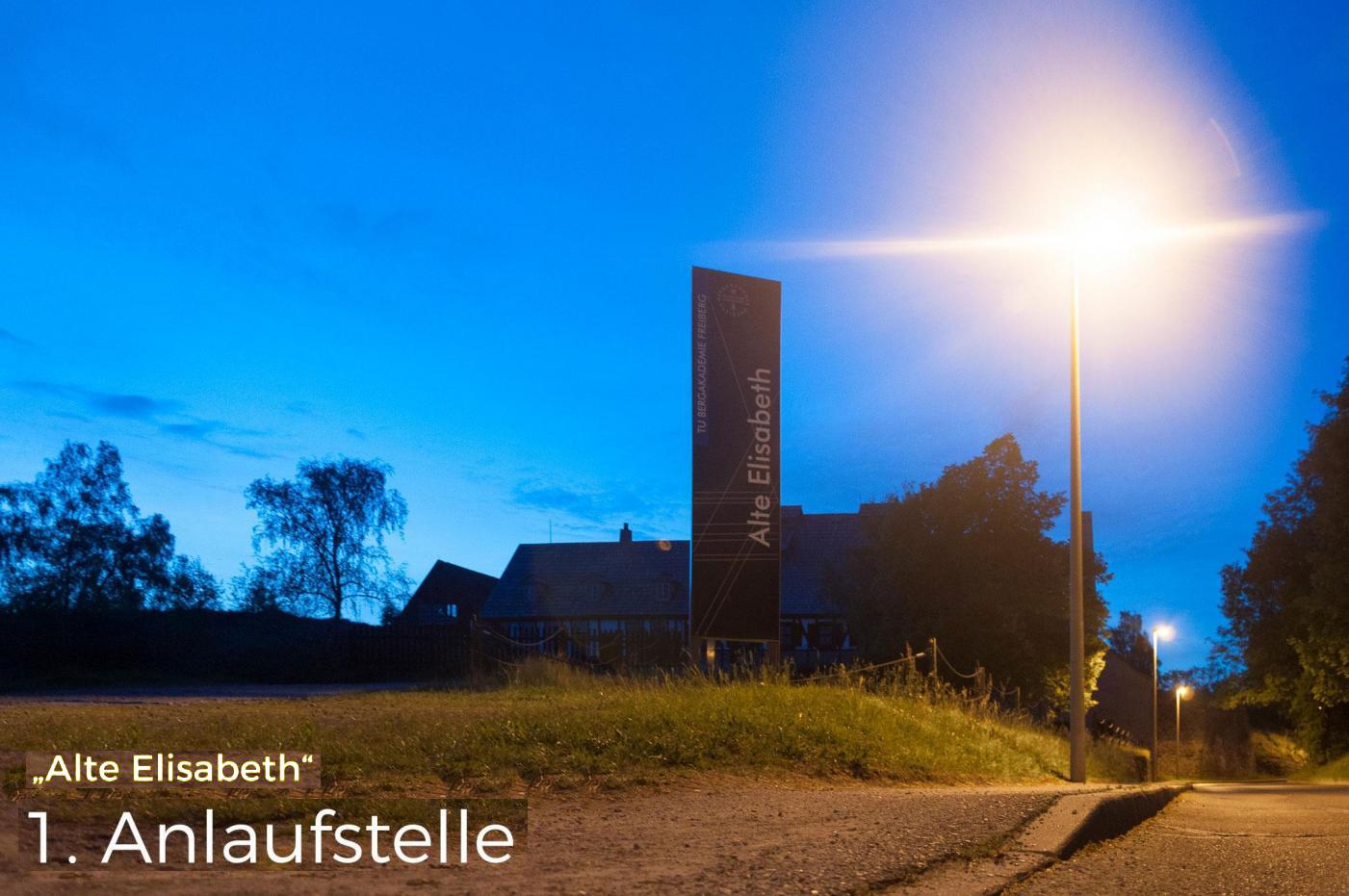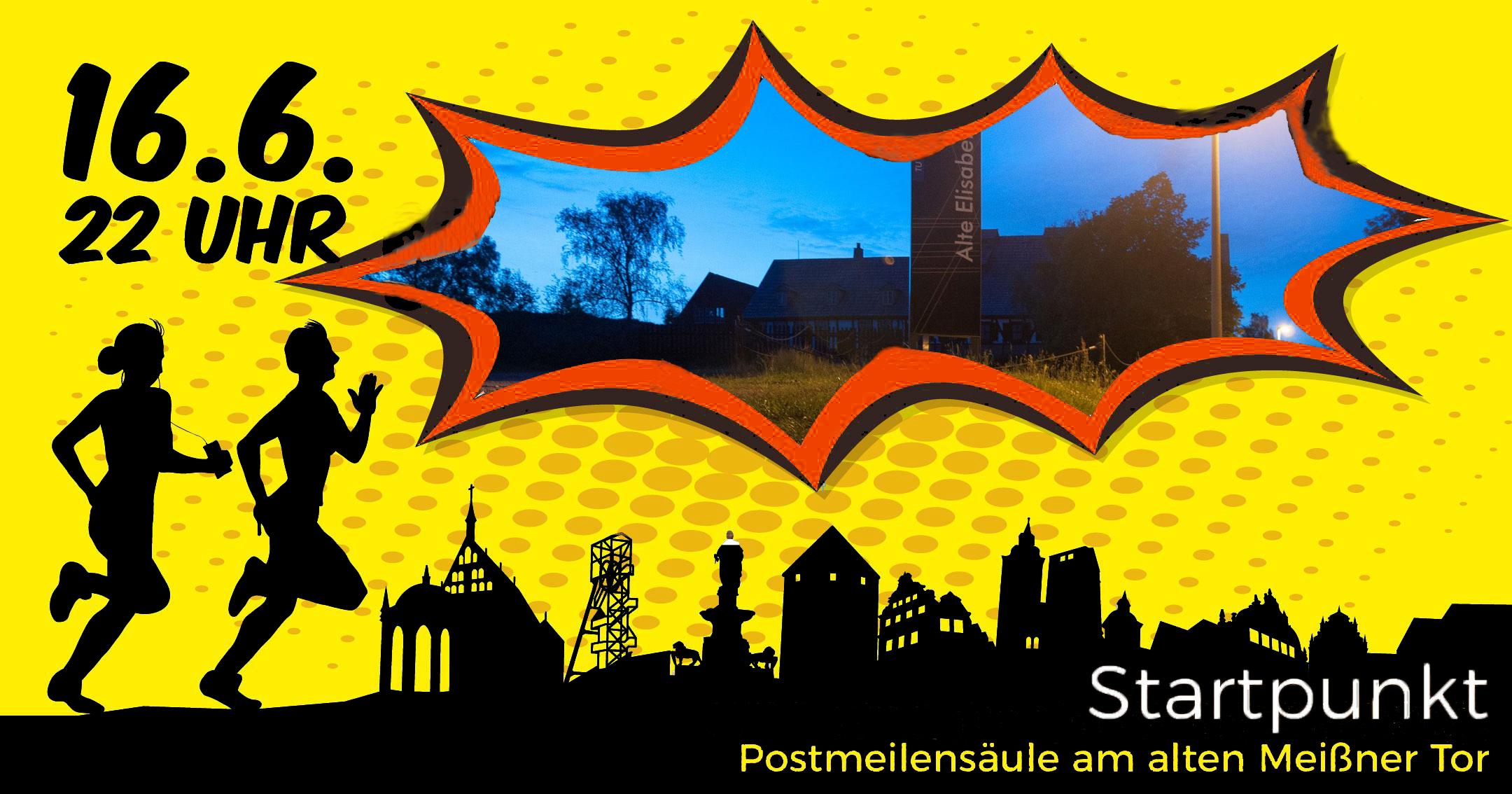
Schrift Midsummer Half
Du scheinst heute mir dieser Farbe auf Kriegsfuß zu stehen.
stimmt :-) Anderer Gelbton oder beides in weiß ? Was meint Ihr?
Das mit den Anführungszeichen klappt - Danke für den Hinweis. Bleibe ich nun beim Gelb, ändere ich den Gelbton oder beides in weiß? Bin echt verunsichert :-)
Meine beiden Cent: Reihenfolge umdrehen, dann kippt der Text nicht so, und komplett weiß setzen.
Das mit den Anführungszeichen klappt - Danke für den Hinweis. Bleibe ich nun beim Gelb, ändere ich den Gelbton oder beides in weiß? Bin echt verunsichert :-)
Wie sieht das denn im Kontext aus?
Meine beiden Cent: Reihenfolge umdrehen, dann kippt der Text nicht so, und komplett weiß setzen.
Mache ich so - Danke!  Beide weiß, die Reihenfolge umgedreht und keinen Hintergrund.
So?
Nein, so nicht. Der »Zusammenhang der Typo und Bildsprache mit der von deinem Plakat« entsteht nicht, indem man einfach einen Aufkleber draufpappt.
Man könnte direkt vom Plakat ausgehen und die Fotos der Anlaufstellen darauf irgendwie integrieren. Vielleicht wäre es einen Versuch wert, den oberen gelben Teil des Plakats mit der Silhouette so zu lassen und statt des Schriftzugs »Mittsommerlauf Freiberg« die Fotos der Anlaufstellen in die Sprechblase zu setzen. Und die Bezeichnung der Anlaufstelle käme dann jeweils anstelle des bisherigen Schriftzugs »Halbmarathon …« unten in die Silhouette.
indem man einfach einen Aufkleber draufpappt.
fand ich auch nicht schön :-)
HIer mal noch ein Test in die Richtung Banner, Plakat
Ne, der Mensch würde keine Schlumpf-Intelligenz neben sich dulden. Datt kannste nich machen.
Mache ich auch nicht, ich lasse es jetzt so wie auf dem Foto von bertel
ich lasse es jetzt so wie auf dem Foto von bertel
Die beiden Hintergrundrechtecke sind aber überflüssig. Wenn der Hintergrund nicht dunkel genug oder zu unheitlich für weiße Schrift ist, dann versuch es doch mal mit dem Ebeneneffekt »Schein nach außen«, falls es den in Lightroom gibt. Falls nicht, kannst du z. B. die Textebene unter das Original kopieren, Weiß gegen Schwarz austauschen, die Ebene rastern und dann einen Unschärfefilter drüber laufen lassen und die Deckkraft der Ebene auf 50% fahren. Aber es gibt da verschiedene Wege, so einen Schein nach außen zu erzeugen. Der Schein nach Außen sollte nur möglichst nicht bewusst wahrnehmbar sein. Jedenfalls nicht im Falle deines aktuellen Bildes. Im Zweifelsfall lieber zu wenig als zu viel. Falls du z. B. merkst, dass der Unschärfeeffekt nicht stark genug war, dann geh halt wieder einen Schritt zurück.
Wenn der Hintergrund nicht dunkel genug oder zu unheitlich für weiße Schrift ist, dann versuch es doch mal mit dem Ebeneneffekt »Schein nach außen«
So ungefähr hätte ich es mir vorgestellt:
Naja, das Bild könnte etwas größer sein. Ich würde (mit deiner Idee weiter "gerechnet") die Explosion so groß ziehen, dass sie den Rest der Gestaltung bedeckt, aber hinter der Silhouette der Stadt und hinter den Läufern liegt.
Dadurch wäre dann auch das Bild größer :-).
Die Idee find ich gut, Dieter. Aber eine professionelle Umsetzung wäre aufwendig. Ich finde nämlich, dass der fotorealistische Hintergrund dem stilisierten Vordergrund in Bezug auf die dargestellten Gebäude, Landschaft u. s. w. entsprechen sollte. Zumindest aber sollten sich die Gebäude einigermaßen ähneln. Das wirklich gut zu realisieren, übersteigt vermutlich die derzeitigen Fähigkeiten von Heike & Stefan. Zumindest will er aber nach eigenem Bekunden den Aufwand in recht engen Grenzen halten.
Außerdem sollte der von der Explosion freigelegte Bildausschnitt des Hintergrundes für die Einheimischen erkennbar sein, und zwar ohne erst zehn Sekunden überlegen zu müssen. Okay, die Säule ist beschriftet. Das macht die Lokalisierung einfach. Auf mich wirkt der freigelegte Bildausschnitt dennoch zu klein.
Das Erste, was ich dachte, sah ich den ja eckt klasse gewordenen Banner mit den in die "Explosion" hinein geprügelten Fotos: "Ne, das geht gar nicht!" Ich finde, das ist einfach nur noch gewollt.
Die Bilder benötigen das nicht, ich finde, weniger ist hier einfach mehr und irgendwie professioneller. Einfach nur die Fotos, weiße Schrift, was da ist und wenn die Weiße Schrift droht, über hellen Stellen im Bild unleserlich zu werden, der Schrift einen zarten Schatten geben.
catfonts hat schon Recht, die Fotos benötigen das nicht. Mir ging es nur um die Einheitlichkeit bzw. den Wiedererkennungseffekt mit dem bisherigen Plakat. Vielleicht sollte man unten nur die Läufer auf schwarzem Untergrund stehen lassen und die Silhouette weglassen, sonst konkurriert das zu stark mit dem Foto. Und das Foto darf auf jeden Fall größer werden und auch vom gezeigten Ausschnitt her kann man das wohl verbessern. Vielleicht muss die Explosion auch nicht genau die jetzige Form haben, sodass sich für den Fotoausschnitt günstigere Proportionen ergeben.
Der Gedankenstrich zwischen Mittsommerlauf und Freiberg gehört raus
Ist ein Link auf Facebook zur Seite und so geht das nicht ohne :-) Der Rest ist korrigiert ... Danke!
Dann würde ich da statt
Mittsommerlauf-Freiberg
lieber
Freiberg-Mittsommerlauf
draus machen, schließlich gibt es ja kein spezielles Freiberg, das nur während des Mittsommerlaufs existiert, sondern es geht hier eben um einen ganz speziellen Mittsommerlauf, den es so eben nur in Freiberg gibt.
Das ist doch so ähnlich als würdest du "Schnitzel-Kalb mit Salat-Kartoffel" anbieten